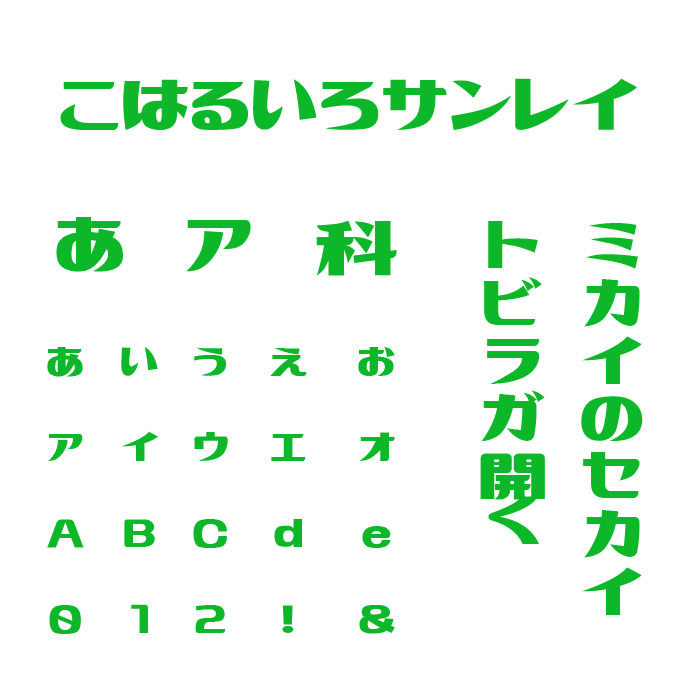
「こはるいろサンレイ」フォントは、アニメ『きんいろモザイク』のロゴからインスパイアを受けて制作された、ユニークかつキュートなデザインフォントです。
アニメのキャラクターたちのポップで可愛らしい雰囲気をビジュアルにしっかりと落とし込んでいます。アニメ関連のデザインはもちろんならが、子供向けのカワイらしいデザインやポップなビジュアルにもマッチする元気なフォントです。
横に長い平体の形状とその太さが特徴なので、フォント自体にダイナミックで元気な印象をもたらしています。ただし、小さいサイズで使用すると文字が潰れて見える可能性があるため、特にロゴやタイトルなど、大きいサイズで見出しなどに取り入れるのがおすすめです。
こはるいろサンレイフォントの文字見本
収録文字は、ひらがな、カタカナ、英数字、一部記号、漢字3351文字が収録されています。